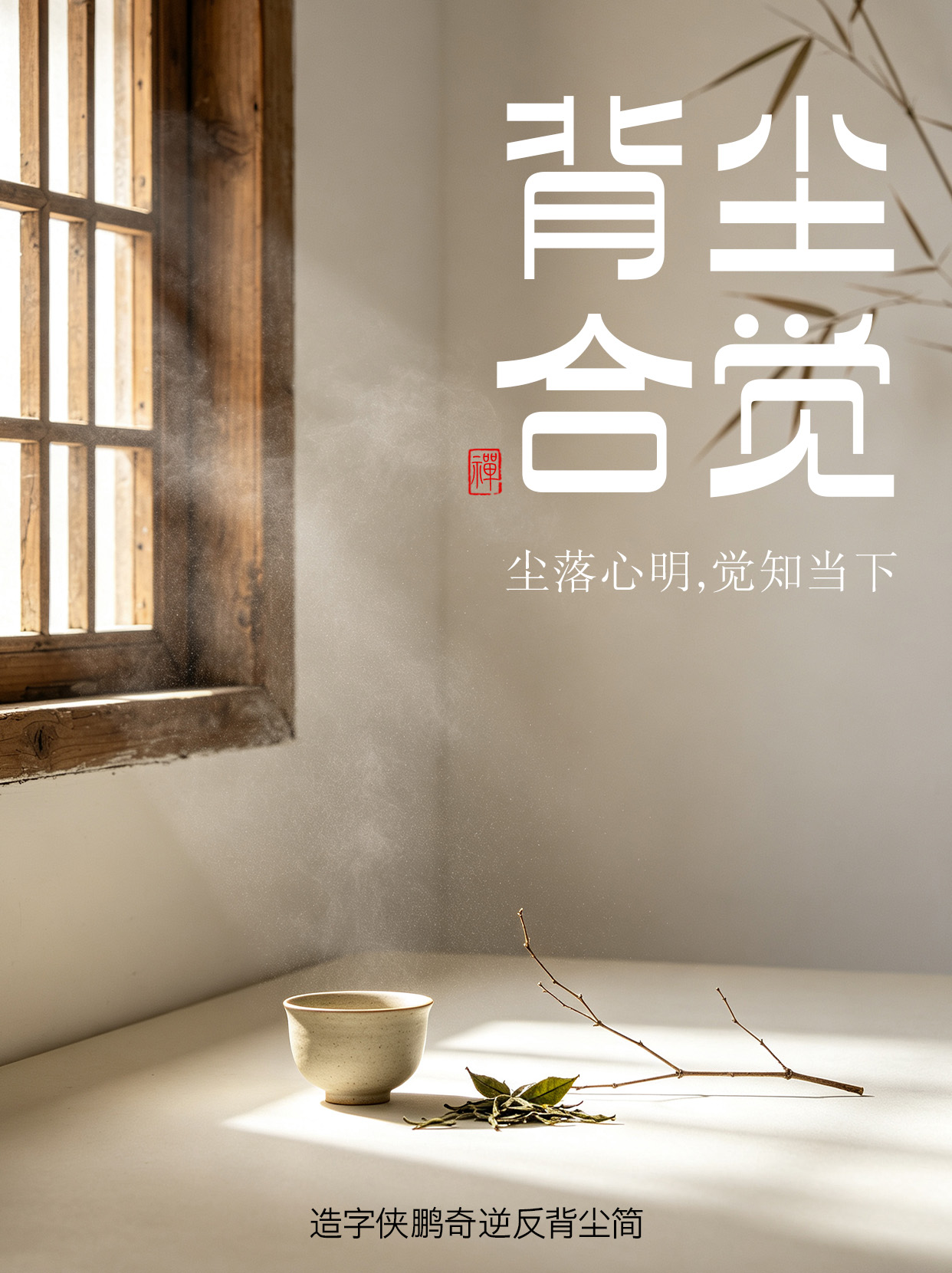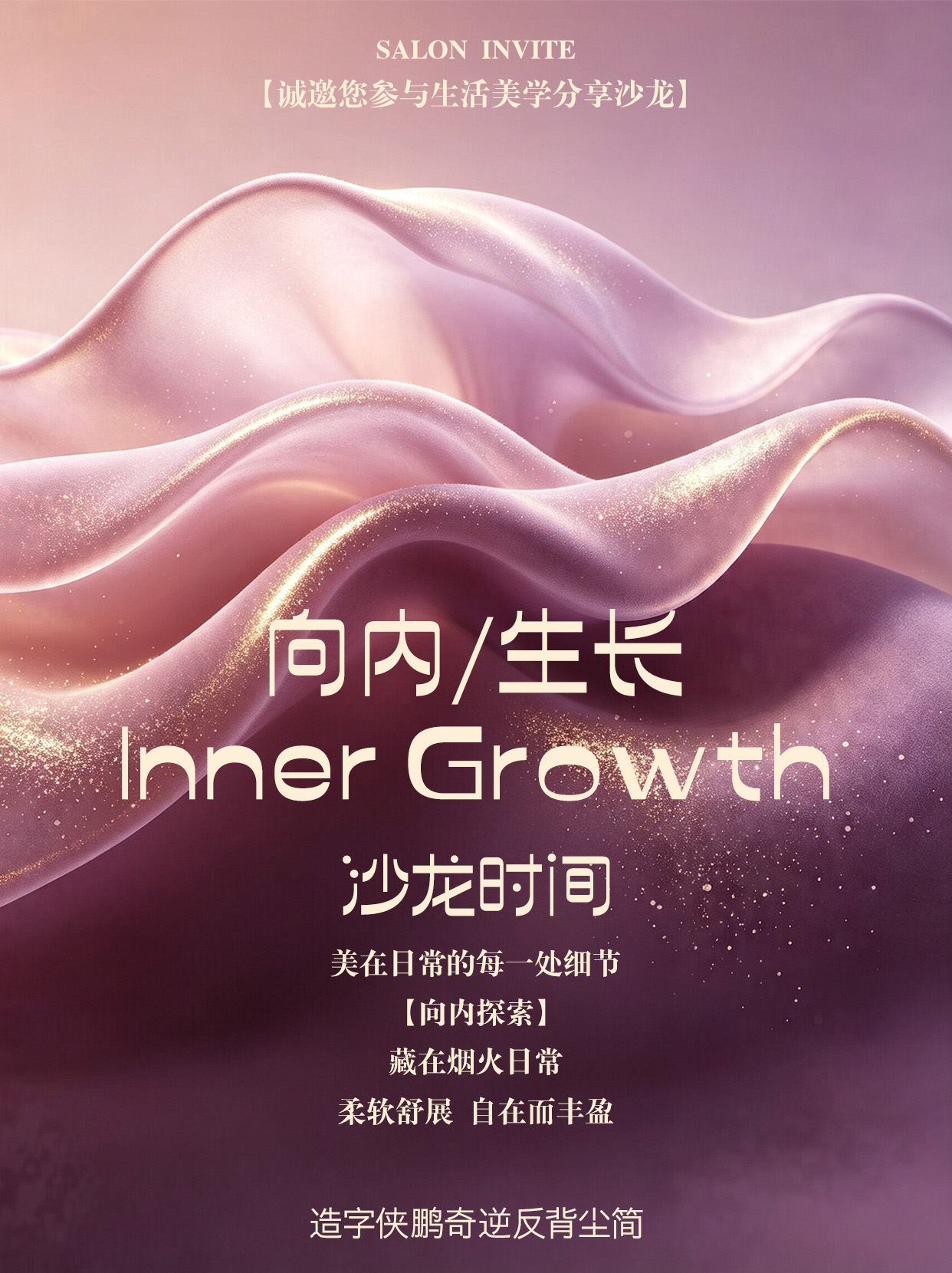
造字侠鹏奇逆反背尘简
PlayFont-BeichenGB
造字侠鹏奇逆反背尘简是一款风格基础、粗细对比适中的逆反差字体,这款字体字形扁宽舒展,10:9 比例沉稳开阔,笔画呈圆角转折,点笔也设计为圆形,温和的叛逆风格与几何的设计细节等特点形成了独特的风格韵味,能适配多种场景进行使用。如潮流品牌、音乐海报、艺术展然及书籍封面等多元场景。